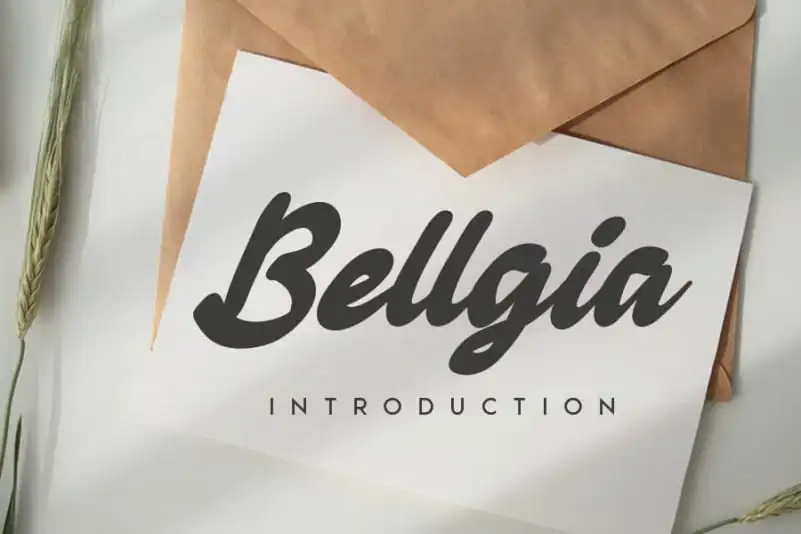
Bellgia Handwritten Font
Bellgia Handwritten Font é uma elegante fonte de escrita manual cuidadosamente criada para tornar-se uma verdadeira preferência. Suas curvas delicadas e toques únicos conferem ao texto um ar casual e descontraído, fazendo com que pareça naturalmente agradável, fácil de ler e extremamente versátil. Esta fonte vai se destacar em qualquer contexto, seja usada sobre fundos coloridos ou como título isolado. Suas linhas finas e detalhes suaves criam um resultado profissional sem perder seu charme pessoal. Experimente Bellgia Handwritten Font para adicionar profundidade e personalidade ao seu design gráfico.